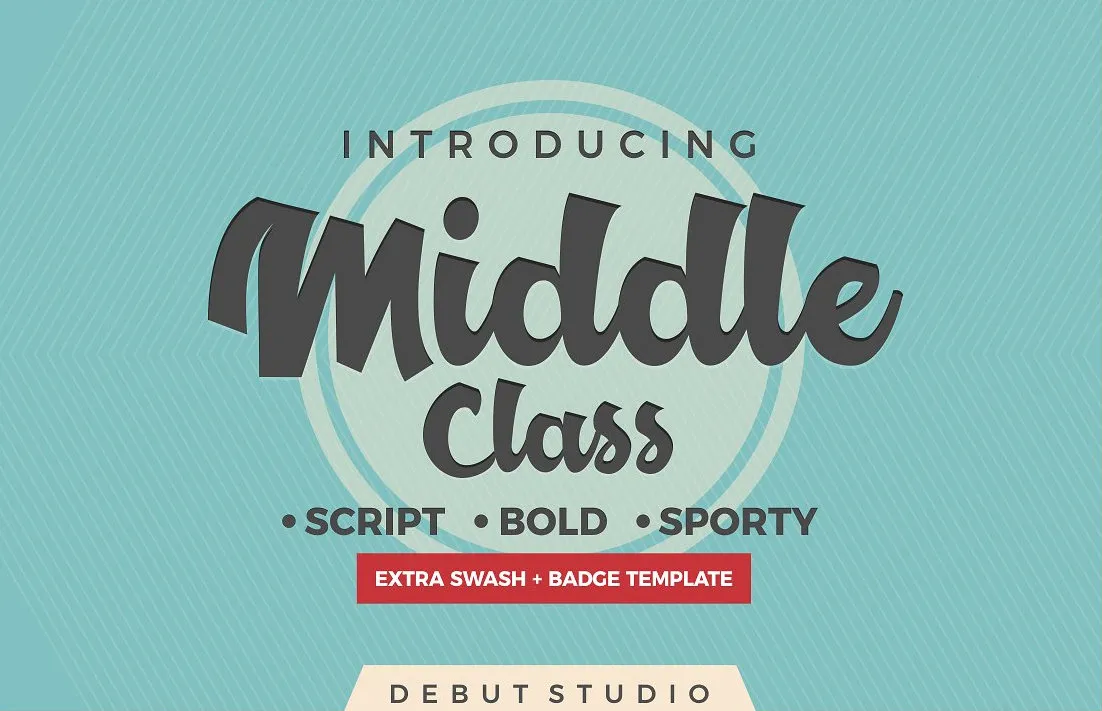
Middle Class Script Font – Download Grátis
Introduzimos a Middle Class! Esta fonte foi projetada pela Debut Studio e é considerada premium. Embora possa ser comprada na Creativemarket, estamos felizes por poder oferecer esta font livremente para download hoje. A Middle Class Script inspirou-se no estilo de letra desenhada à mão e do logotipo, com uma ampla gama de variações em cada caractere incluindo alternativas de opentype, ligaturas comuns e até mesmo swashes adicionais que permitem aos designers personalizarem suas criações. Evidente para uso em logotipos, cabeçalhos de carta, postais, design para roupas, etiquetas e muito mais.